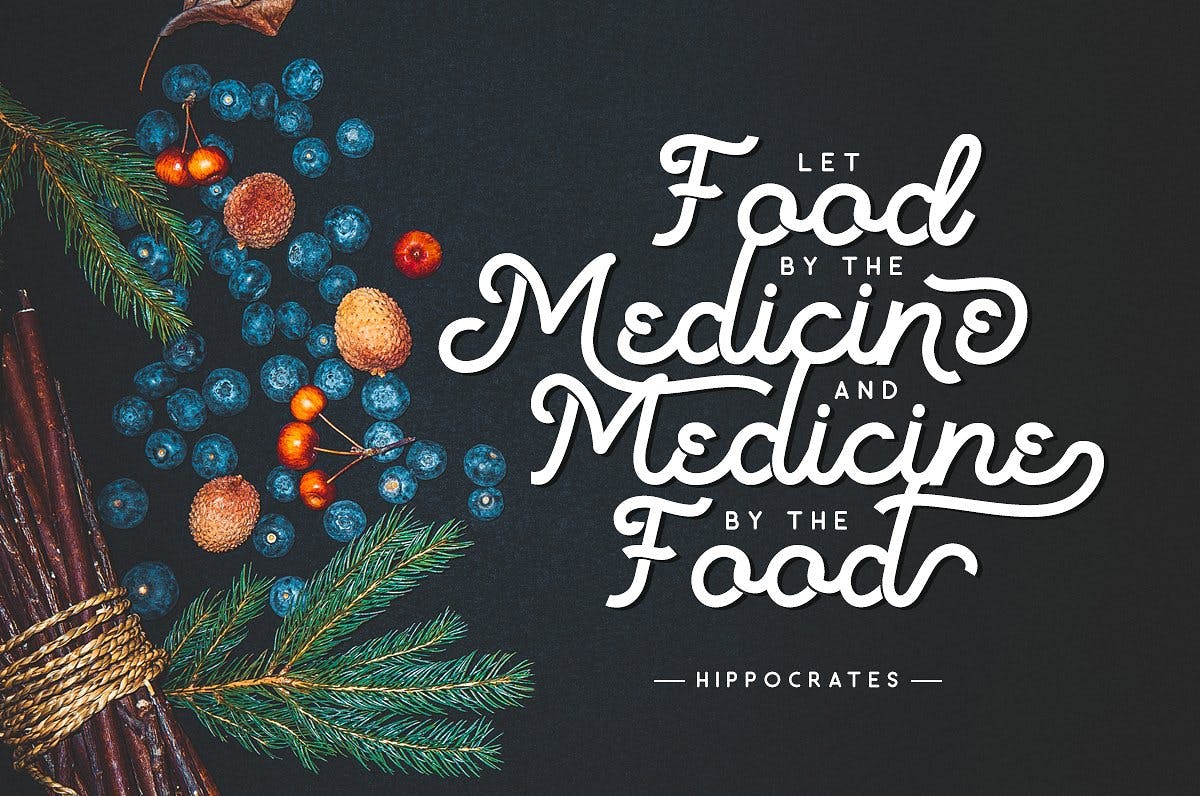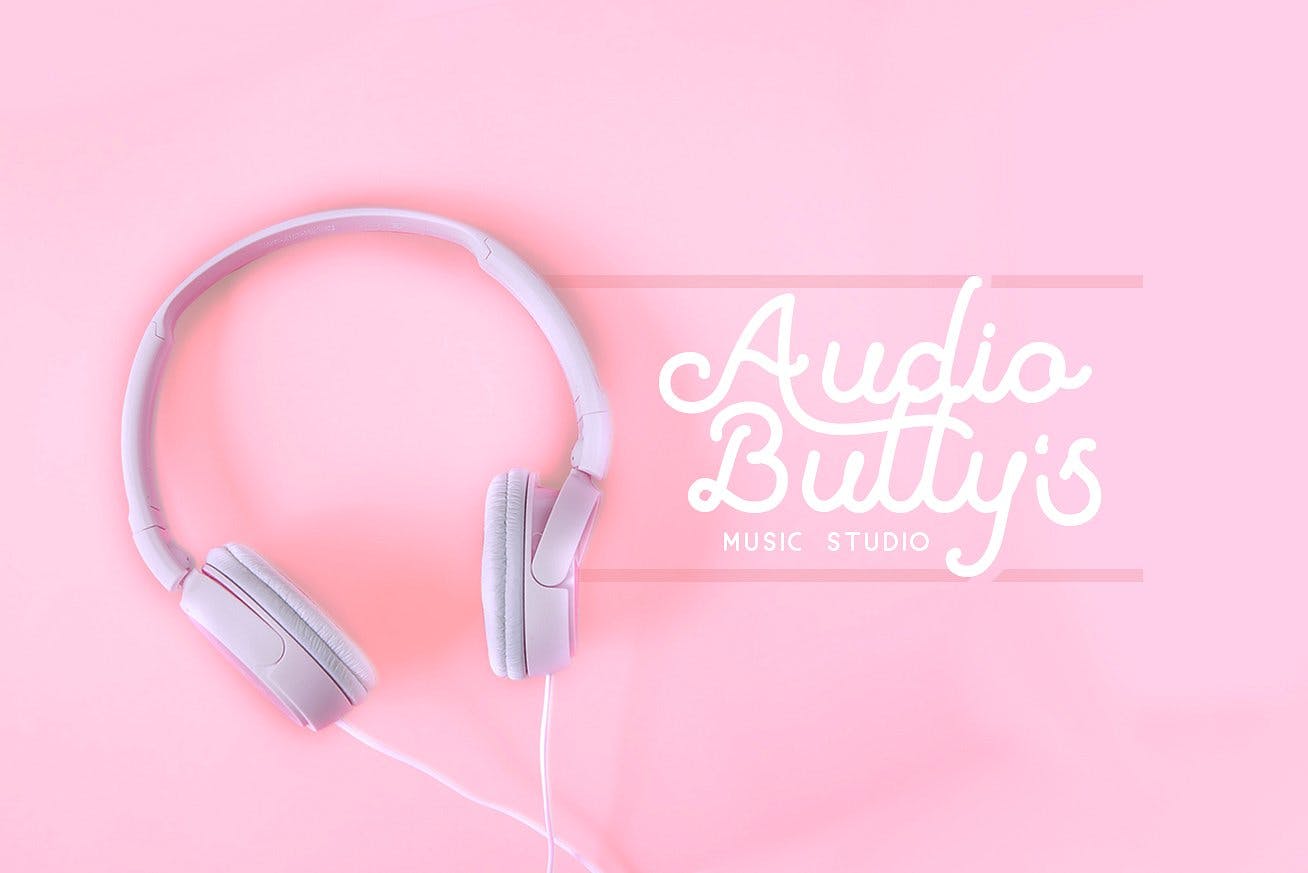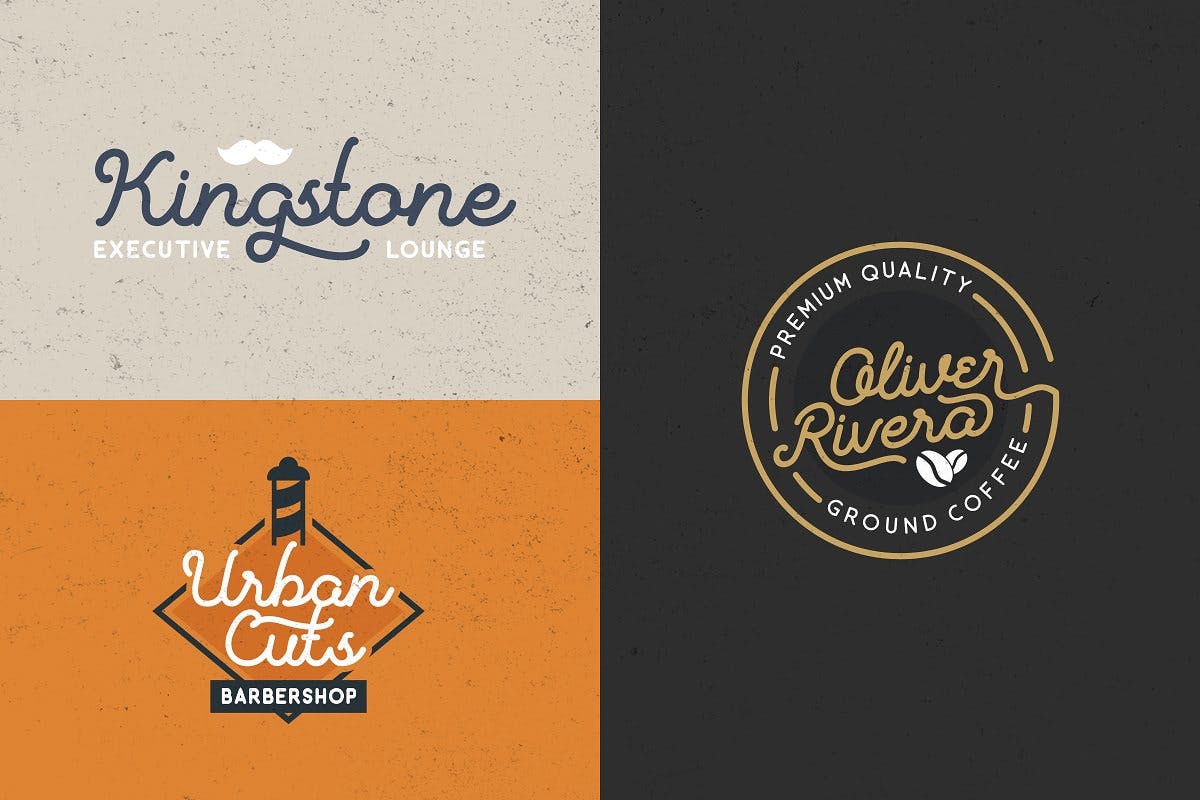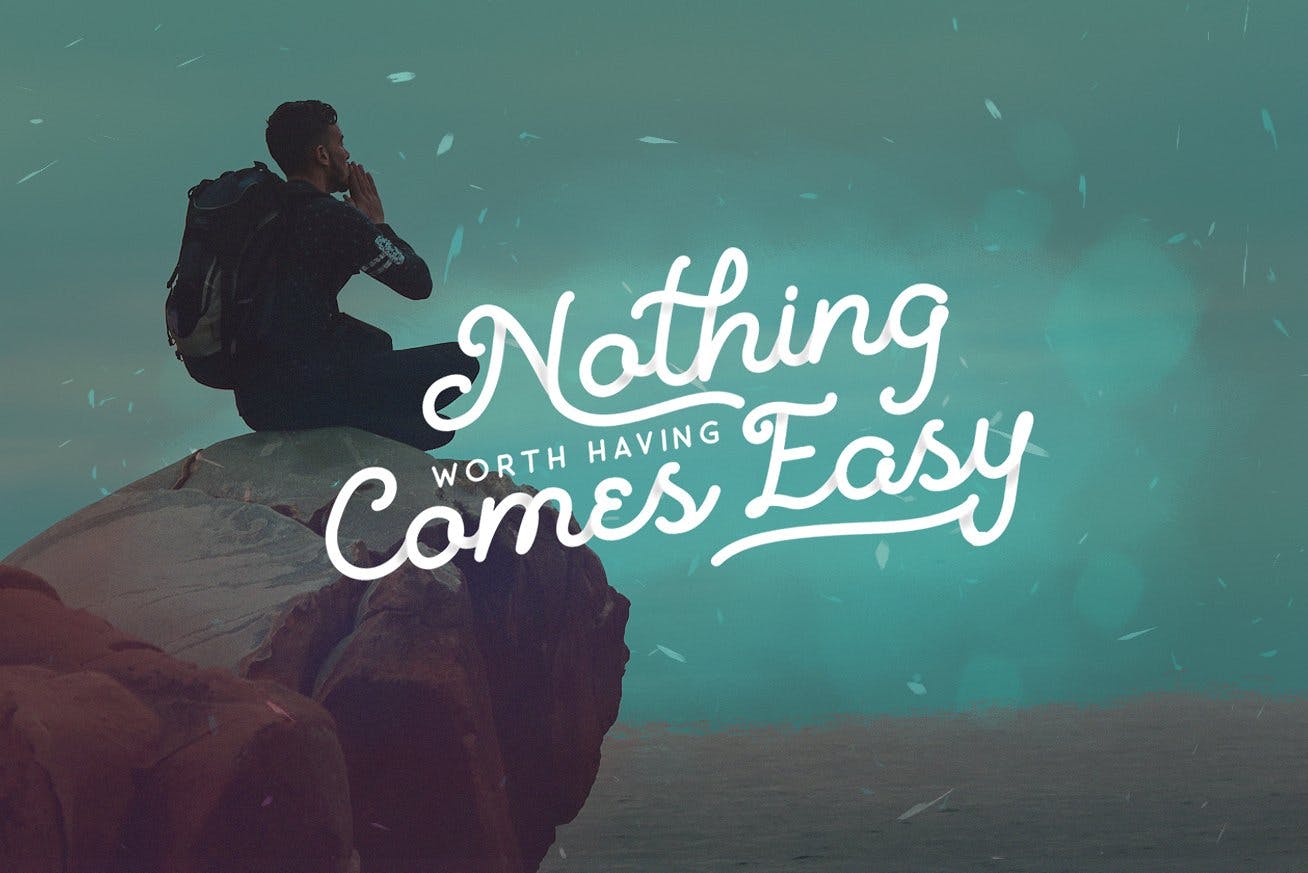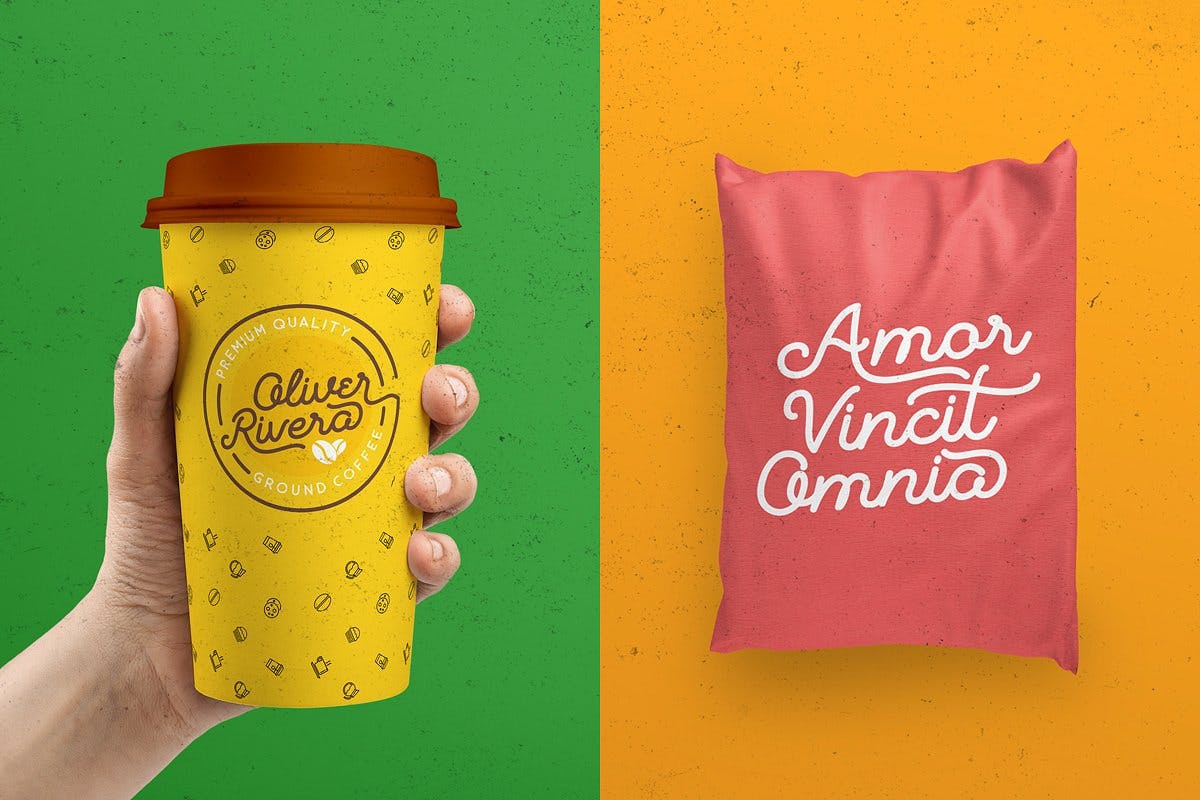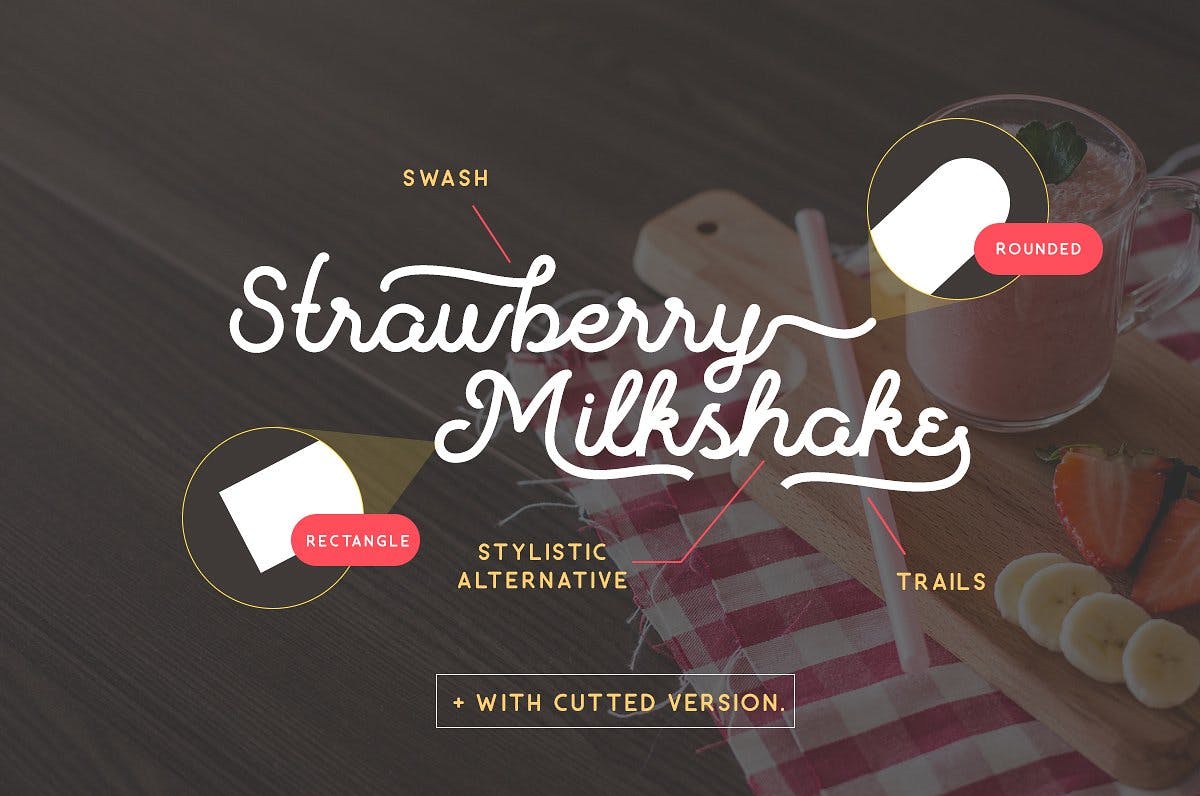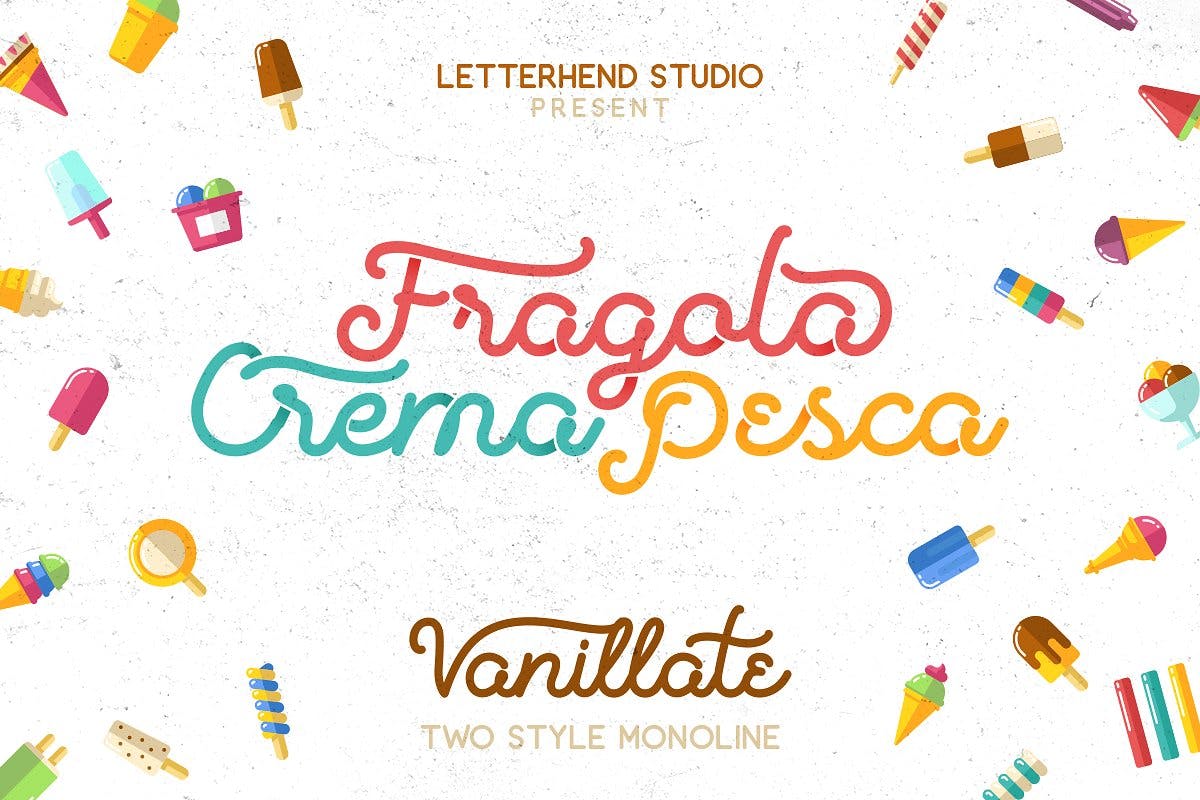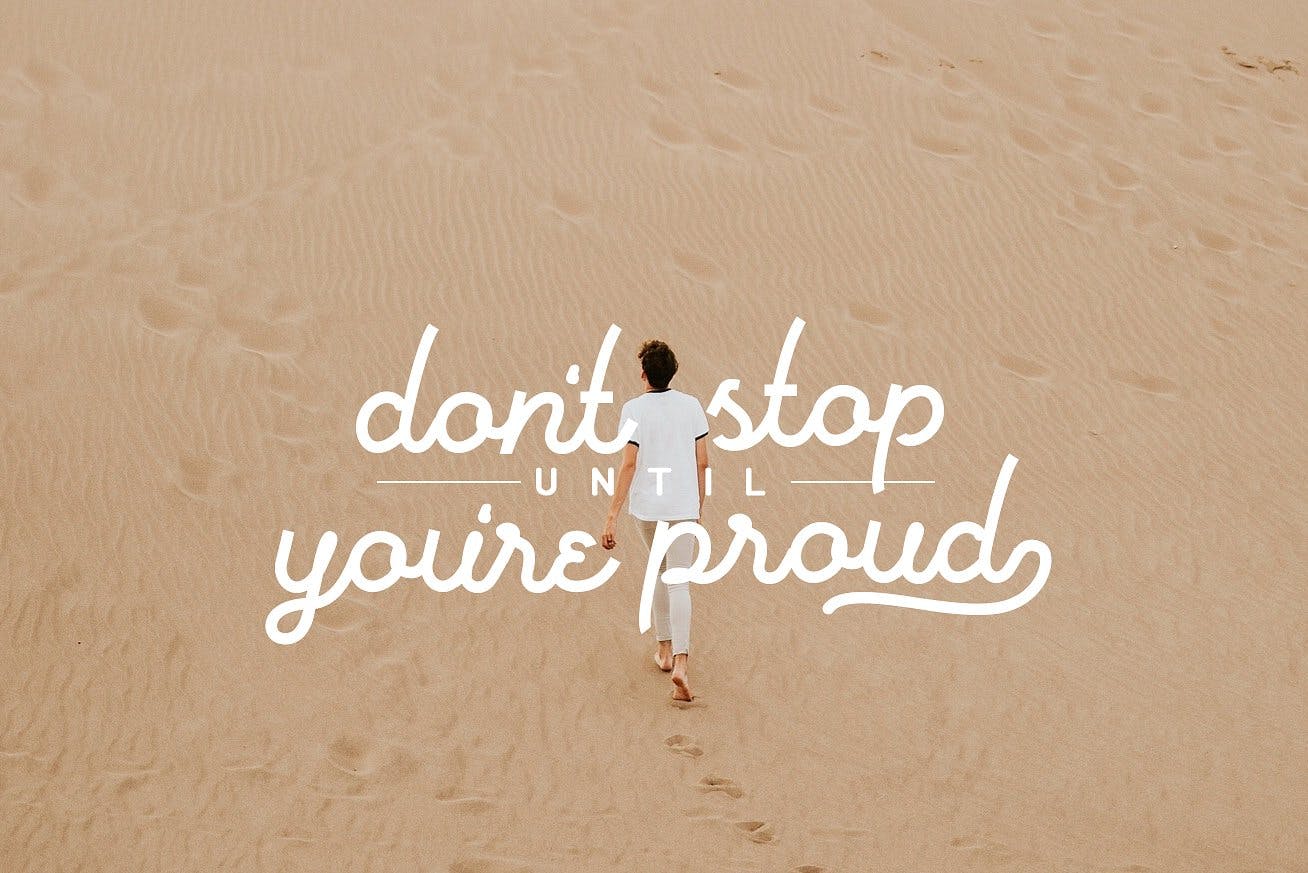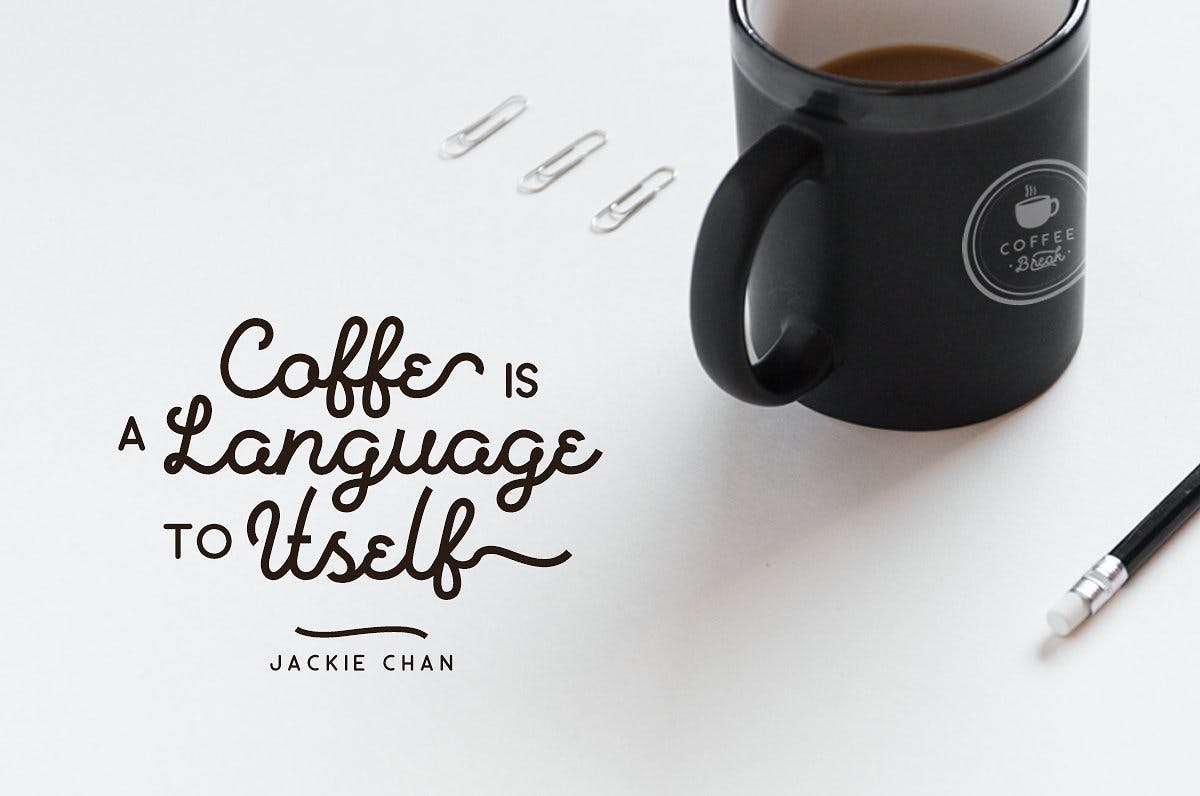
Vanilatte Font Duo
فونت دوگانه Vanilatte، یک نوع فونت مونو لاین منحصر به فرد است که شامل دو سبک مختلف می‌باشد. این فونت شامل حروف بزرگ، کوچک، نشانه‌گذاری، نمادها و اعداد، مجموعه‌های استایلیستیک جایگزین، و لیگاتورها است. همچنین ما یک فونت سانس به عنوان مکمل اضافه کرده‌ایم و 15 قالب لوگو آماده با تم غذایی نیز در اختیار شما قرار داده‌ایم!
• مناسب برای طراحی‌های گرافیکی و لوگوها
• شامل حروف بزرگ و کوچک
• شامل 15 قالب لوگو آماده
• قابل استفاده در پروژه‌های مختلف طراحی